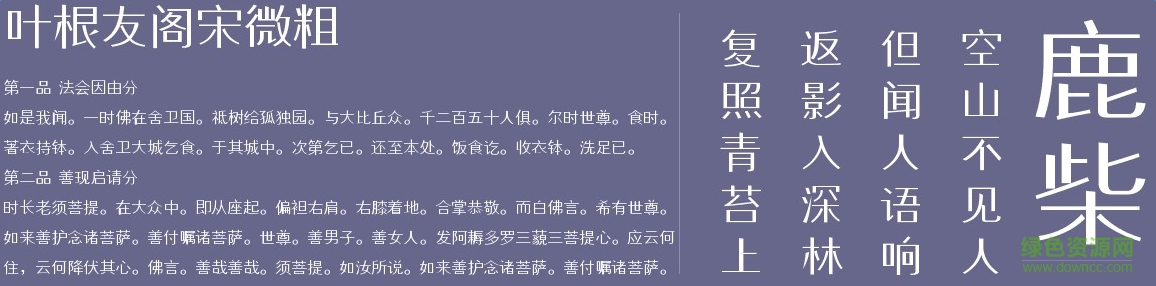
葉根友閣宋微粗
葉根友閣宋微粗是一款由知名書法家葉根友創(chuàng)造的字體,適用于廣告、藝術(shù)設(shè)計,海報設(shè)計等方面,美工朋友們不要錯過了。小編為大家提供免費下載地址。歡迎大家來綠色資源網(wǎng)踴躍下載哦!
官方介紹
葉根友閣宋微粗,一款經(jīng)典的細體風格的字體,所有葉根友系列字體中筆畫最細的字體,適合內(nèi)文排版,手機系統(tǒng),內(nèi)嵌程序等應用。
葉根友閣宋微粗
小編點評
葉根友閣宋微粗,用途廣泛,是葉根友先生的印刷字體,字體以宋體字為原型加以打磨變化,適用于文字排版等方面。各位字體收藏者可以來看看。